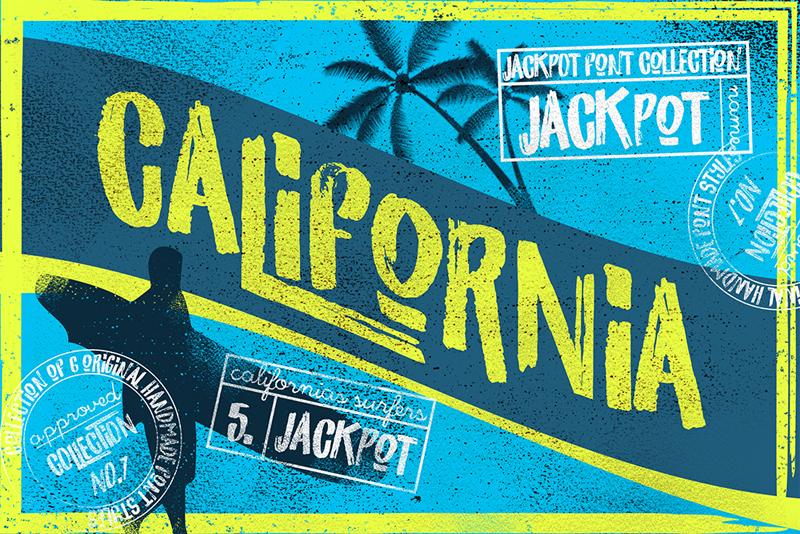
California Brush Font – Download Grátis
Aqui está uma versão em português do Brasil, envolvente e natural, para a descrição de uma página de download para a fonte ‘California Brush Font’: A fonte “California Brush” surge repleta de energia, com traços rápidos e lados agudos. Ela é perfeita para mensagens agressivas ou vibrantes. A California Brush é um alimento para os olhos que se destaca quando você precisa criar uma identidade visual dinâmica. É uma escolha ideal para vários usos, desde logomarcas e tags personalizadas até frases em estilo de arte livre ou citações escritas à mão. É perfeitamente adequada para embalar sua marca nas embalagens de produtos e mercadorias. Também é excelente para criar designs para camisetas e outros produtos de roupas. Para aqueles que desejam um visual mais informal e criativo, a fonte “California Brush” se torna uma ferramenta versátil e divertida para ilustrar cartões de felicitações e páginas nas redes sociais. Seja você um designer ou simplesmente alguém que gosta de criar conteúdo original, esta fonte é uma maneira incrível de deixar seu estilo mais atraente e único. Composta com rapidez e sutileza em cada traço, a California Brush mantém a essência vibrante e moderna do design gráfico contemporâneo. Esteja pronto para transformar suas criações em obras memoráveis através da escolha certa de uma fonte única.